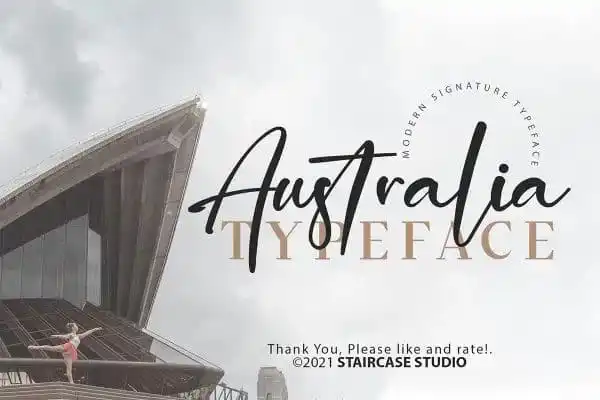
Australia Script Font – Download Grátis
Australia Script Font é uma fonte de script moderna criada pela Staircase Studio. Ela traz elegância, luxo e modernidade para qualquer projeto onde você deseja dar destaque a seus textos. Com sua coleção extensa de letras e números perfeitos para projetos, o Australia Script Font também é ótimo para logotipos, design de marca, criação de logotipo, arte digital de letra, roupas e camisetas digitais, cartazes, publicações, sinalização e design de anúncios. Este fonte oferece uma ampla gama de opções que atende a qualquer necessidade criativa em seu próximo projeto. Não perca tempo: transforme seus projetos em verdadeiras obras de arte com o Australia Script Font da Staircase Studio.